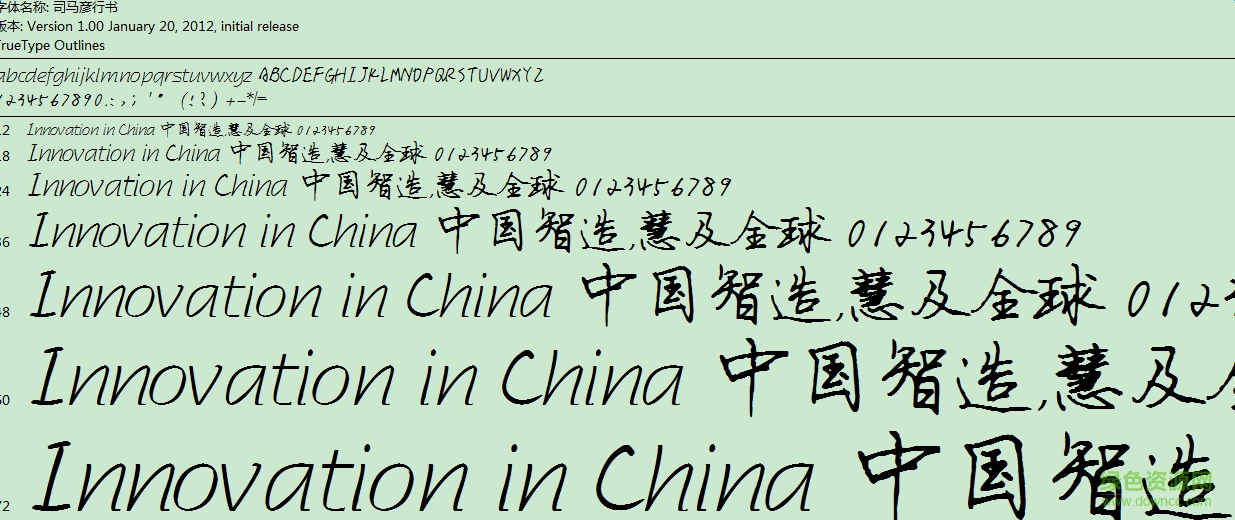
司馬彥行書字體是一款簡體字體,用途廣泛,文字排版、海報廣告設(shè)計、美術(shù)設(shè)計等方面都可以使用,有需要的朋友不要錯過了,歡迎大家來綠色資源網(wǎng)踴躍下載哦!
司馬彥行書字體,它在楷書的基礎(chǔ)上發(fā)展起源的,介于楷書、草書之間的一種字體,是為了彌補楷書的書寫速度太慢和草書的難于辨認(rèn)而產(chǎn)生的。